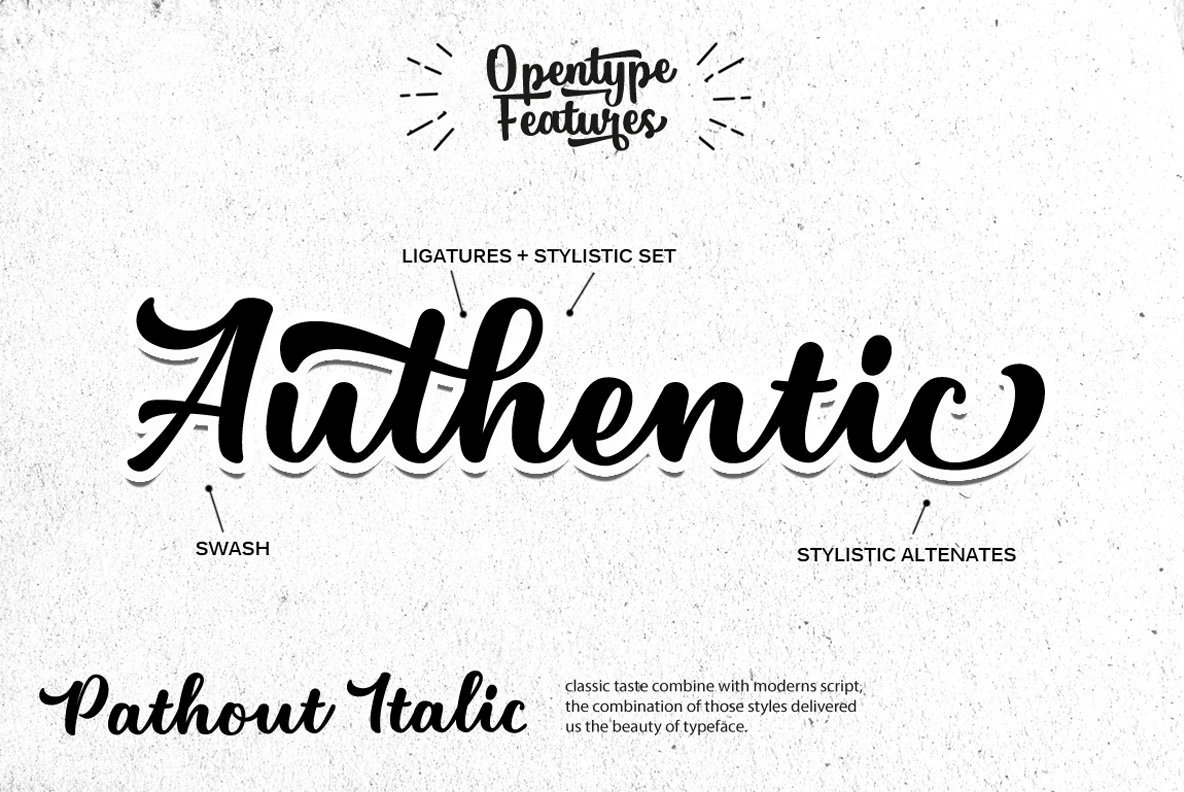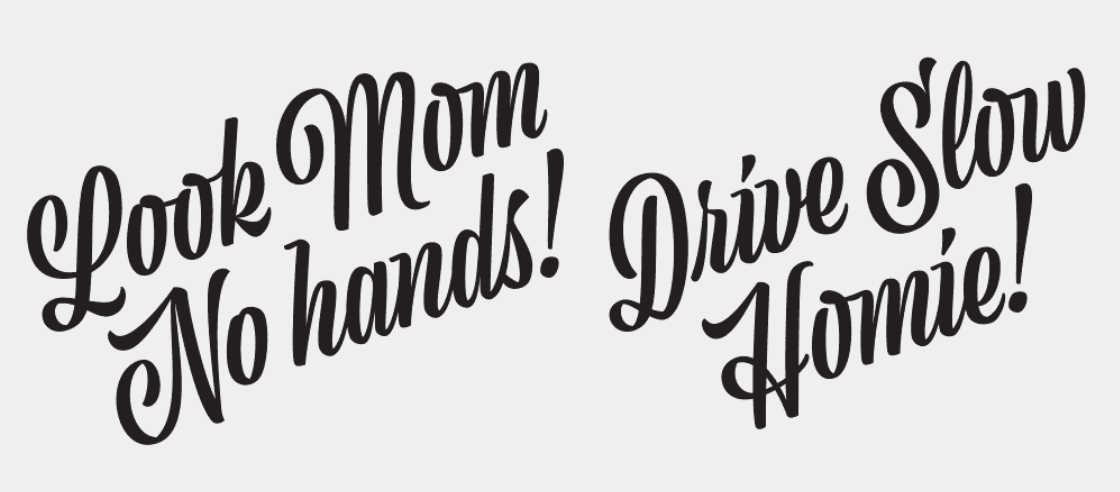
30+ Бесплатных рукописных шрифтов | by Writes
С новыми трендами на типографику дизайнеры все больше и больше нуждаются в уникальных шрифтовых сочетаниях.
Шрифтов не бывает много, тем более рукописных. Именно поэтому мы сделали подборку крутых, рукописных шрифтов. Все шрифты бесплатны и готовы к использованию.
Кириллица там тоже есть!
33 свежих бесплатных шрифта для веб-дизайнера 2017
Сегодня у меня свежая, 2017 года подборочка классных бесплатных шрифтов для веб-дизайна и не только.
Я не стала делить ее на разные подрубрики типа: шрифты рукописные, шрифты гранжевые, шрифты ретро и т.п. Думаю, вы сами разберетесь, кто есть ху.
Естественно, я выбирала все больше рукописные, гранжевые и винтажные шрифты, т.к. сама их очень люблю.
Предвосхищая стандартный вопрос, говорю сразу: кириллицы там нет. Да и не всегда она смотрится так же выразительно, как латиница. У каждого языка есть свои выгодные стороны и наоборот — не самые красивые детали. Но если кому-то очень нужно использовать эти шрифты для отображения кириллицы, то фотошоп вам в очумелые ручки и вперед! 🙂
1. Fibre — бесплатный жирный винтажный шрифт
2. King Basil — бесплатный рукописный шрифт-кисточка
3. Humger — стильный гранжевый потертый шрифт
4. Zviro — симпатичный и элегантный шрифт с засечками
5. Black Mask — рубленный брутальный шрифт с засечками в стиле гранж
6. Westfalia — бесплатный рукописный лаконичный кисточковый шрифт
8. Monk — универсальный бесплатный шрифт для логотипов
9. Metro Grunge — уникальный и очень красивый гранжевый шрифт
10. Bajern — бесплатный и элегантный шрифт под готику
11. Black Willow — бесплатный «мелковый» шрифт под леттеринг
12. Setta Script — красивый бесплатный рукописный шрифт
13. Caleb — необычный рукописный шрифт для флаеров
14. Sweet Sorrow — классный ретро шрифт
15. Aaminah — очень художественный тонкий рукописный шрифт
16. Befolk — элегантный кисточковый шрифт для леттеринга
17. SickBoy — энергичный рукописный маркерный шрифт
18. Whortle — широкий рукописный маркерный шрифт
19. Hello Stockholm — стильный и стремительный бесплатный рукописный шрифт
20. Noelan — современный каллиграфический шрифт для плакатов, флаеров и пр.
21. Old Growth — необычный и красивый шрифт
22. Molleat — бесплатный рукописный кисточковый шрифт
23. Fabulous — шикарный каллиграфический шрифт для леттеринга и пр.
24. Hometown — очень элегантный тонкий шрифт в стиле ретро
25. Chapel Script — бесплатный шрифт в стиле леттеринга
26. Bold & Stylish Calligraphy — красивый каллиграфический шрифт
27. Bardo — классический элегантный ретро шрифт
28. Electronics — бесплатный жирный псевдо-рукописный шрифт
29. Shabrina — свежий и энергичный шрифт в стиле леттеринга
30. Sketch — бесплатный рукописный шрифт в стиле широкая кисть
31. Albondigas — каллиграфический шрифт для леттеринга и пр.
32. Messenger Pigeons — стильный бесплатный каллиграфический шрифт
33. Jumper — отличный маркерный «сухой» бесплатный шрифт
Мы собрали 101 рукописный шрифт, который вы можете бесплатно использовать в любом дизайне. Задайте настроение бренда с помощью каллиграфии.
7. Трагический маркер
Tragic Marker — это толстый рукописный шрифт, который, как следует из названия, напоминает аккуратный и жирный почерк толстого маркера. Шрифт может использоваться в самых разных ситуациях, включая заголовки, электронные поздравительные открытки и дизайны, которые стремятся быть игривыми, но в то же время профессиональными.
8. Сценарий Шраг
Scrag Script будет одинаково хорошо смотреться на веб-сайте DIY или в проектах для школьников — он выглядит теплым и дружелюбным, но, что более важно, он аккуратный и читаемый.
9. Скрипт Mervale